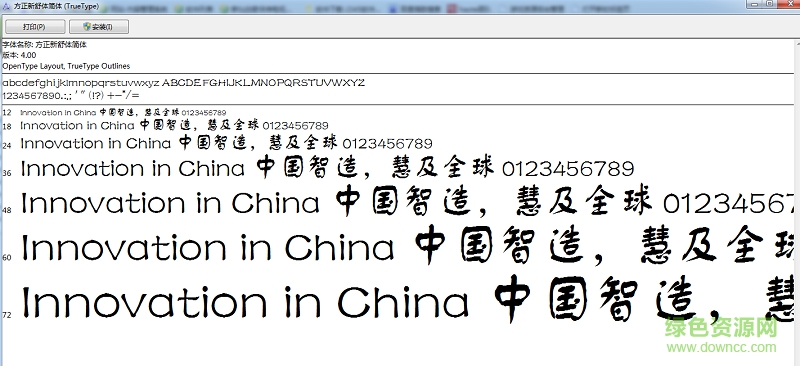
fznstjw字體
fznstjwgb10字體是一款很美觀的字體,這款字體字形飄逸,但是也不像正楷字體那么嚴肅,一筆一劃之間有中活潑的韻味,感興趣的朋友就來綠色資源網下載吧!
fznstjwgb10字體介紹
fznstjwgbk字體是一款方正出品的gbk字體,藝術設計、海報設計、美工等都可以使用,字體簡潔耐看、工整流暢。